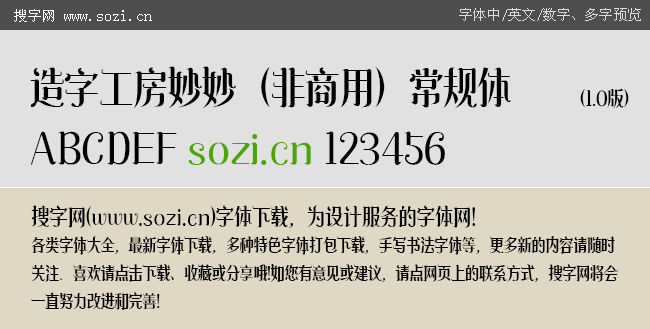
造字工房妙妙(非商用)常規(guī)體
搜字網(wǎng)提供一款造字工房妙妙(非商用)常規(guī)體中文字體下載,造字工房妙妙字體是以造字工房體為原型所創(chuàng)作出的字體,字體獨特的手寫風(fēng)格和俏皮的樣式,使字體看起來個性時尚,整體字體識別性強(qiáng),又很有趣味性。此款字體適用于主副標(biāo)題及個性品牌的設(shè)計等應(yīng)用。